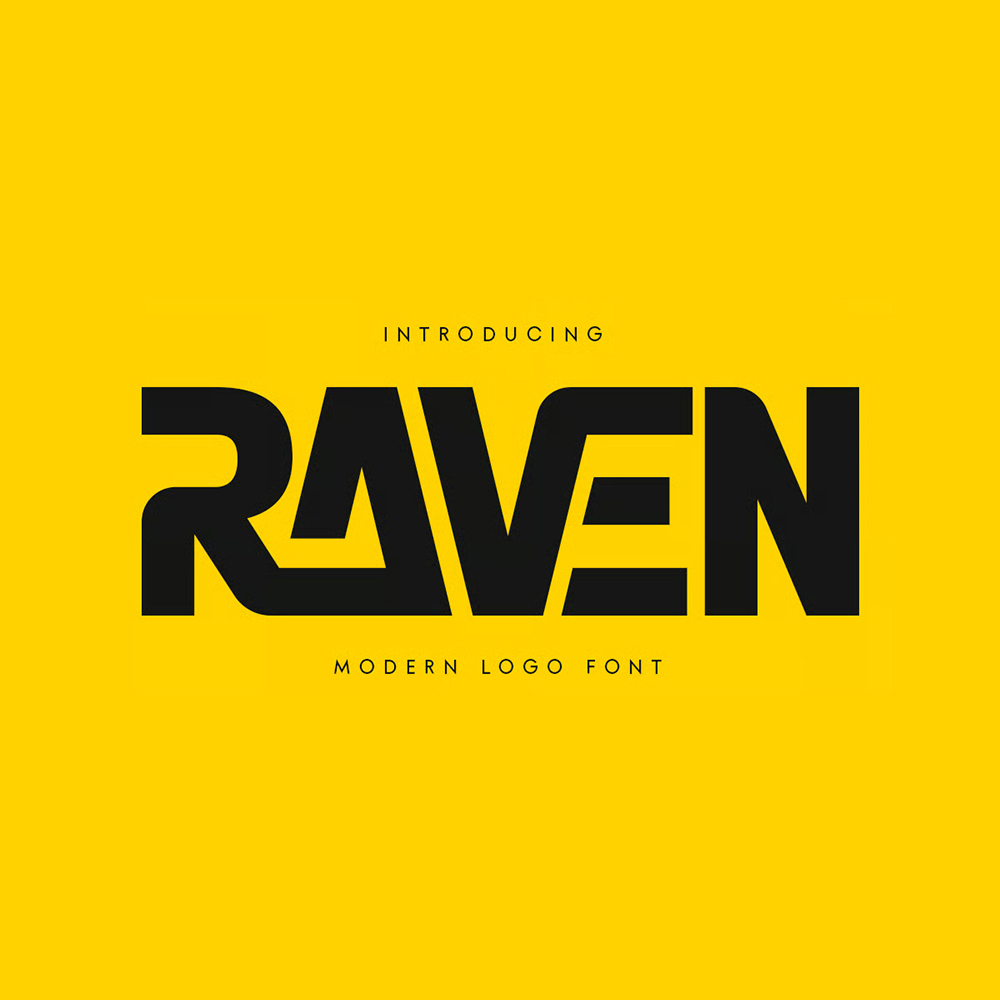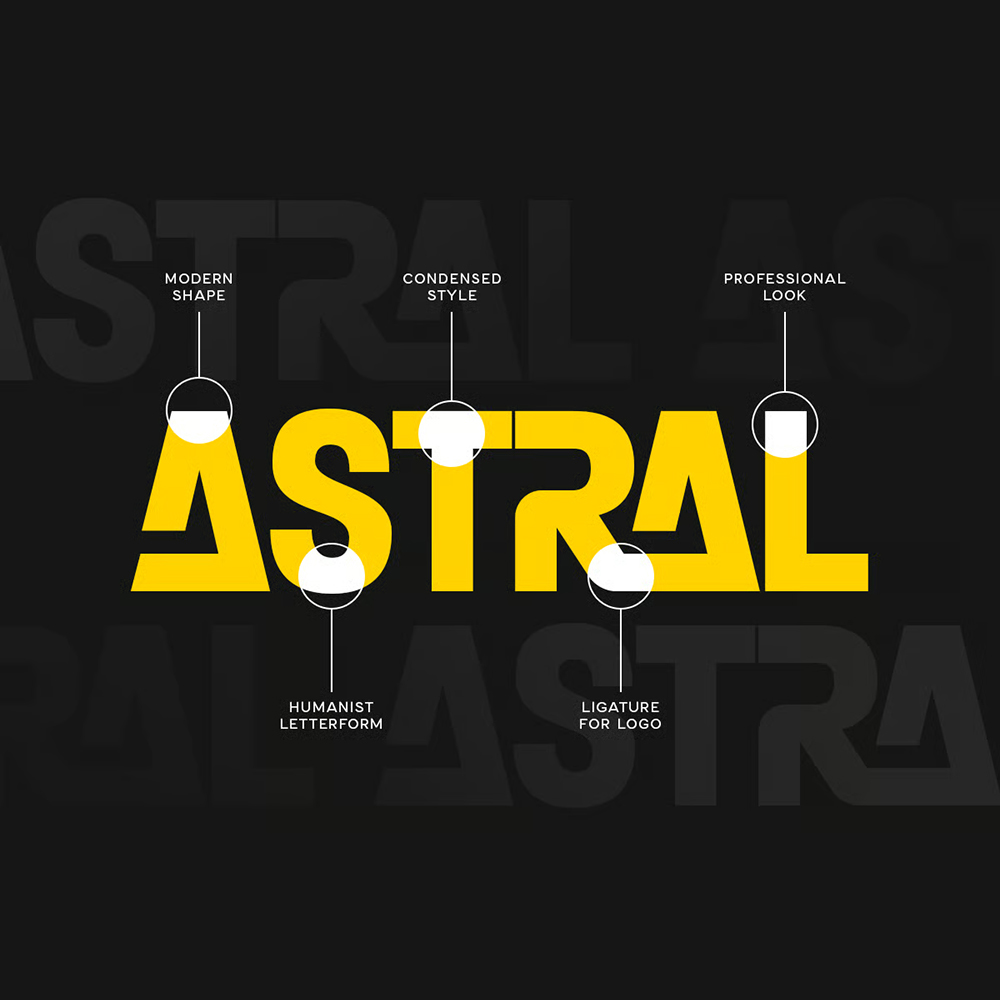
فونت پرمیوم و انگلیسی Raven یک فونت لوگوی مدرن است که برای ارتقای پروژههای برندسازی و طراحی شما با خطوط براق، تمیز و زیباییشناسی جسورانه طراحی شده است. سبک معاصر آن، آن را برای لوگوها، تیترها و هر پروژهای که نیاز به لمس چشمگیر و مینیمالیستی دارد، ایدهآل میکند. اشکال هندسی قوی Raven ظاهری حرفهای و ظریف ایجاد میکند و آن را برای مشاغل مدرن و سرمایهگذاریهای خلاقانه ایدهآل میسازد.
مزایای استفاده از فونت لاتین Raven Font چیست؟